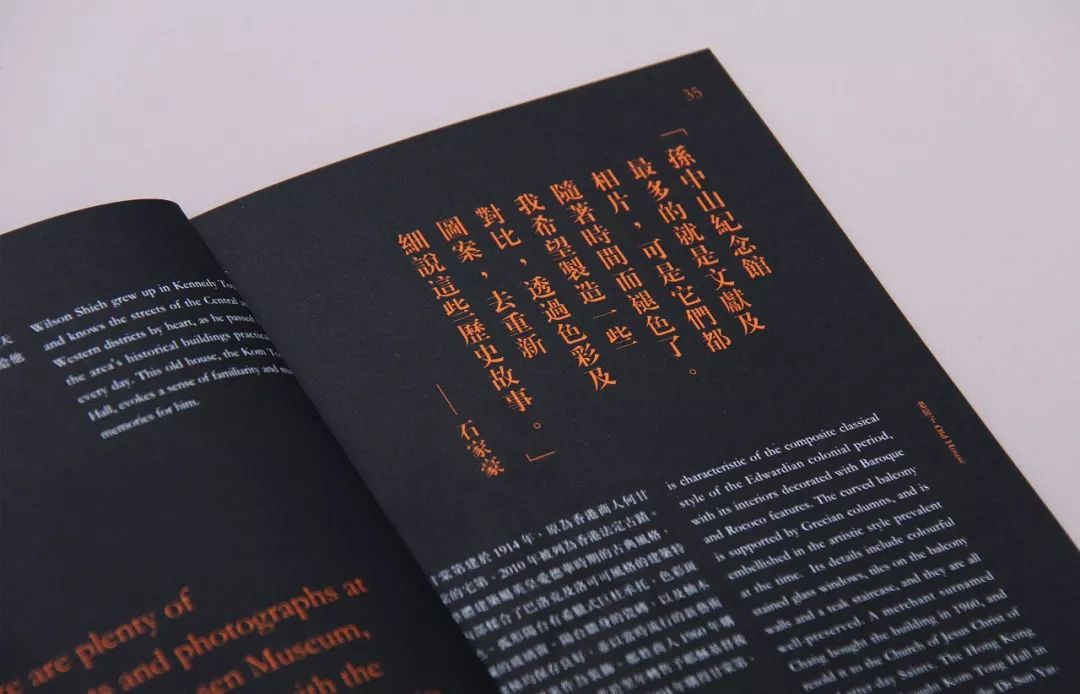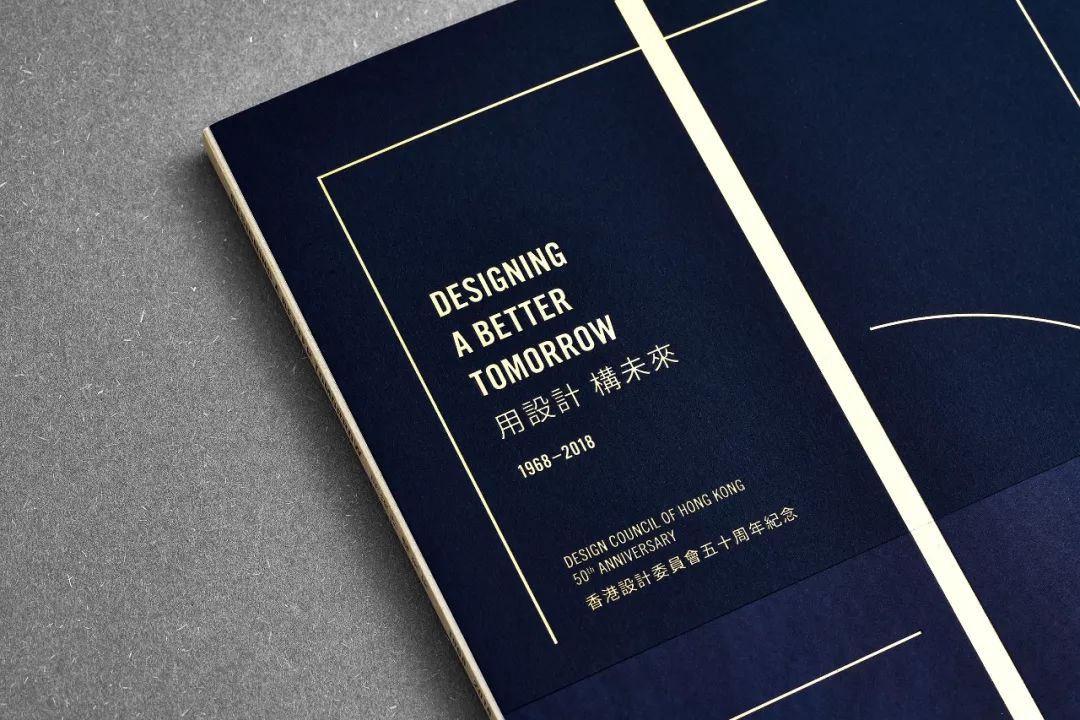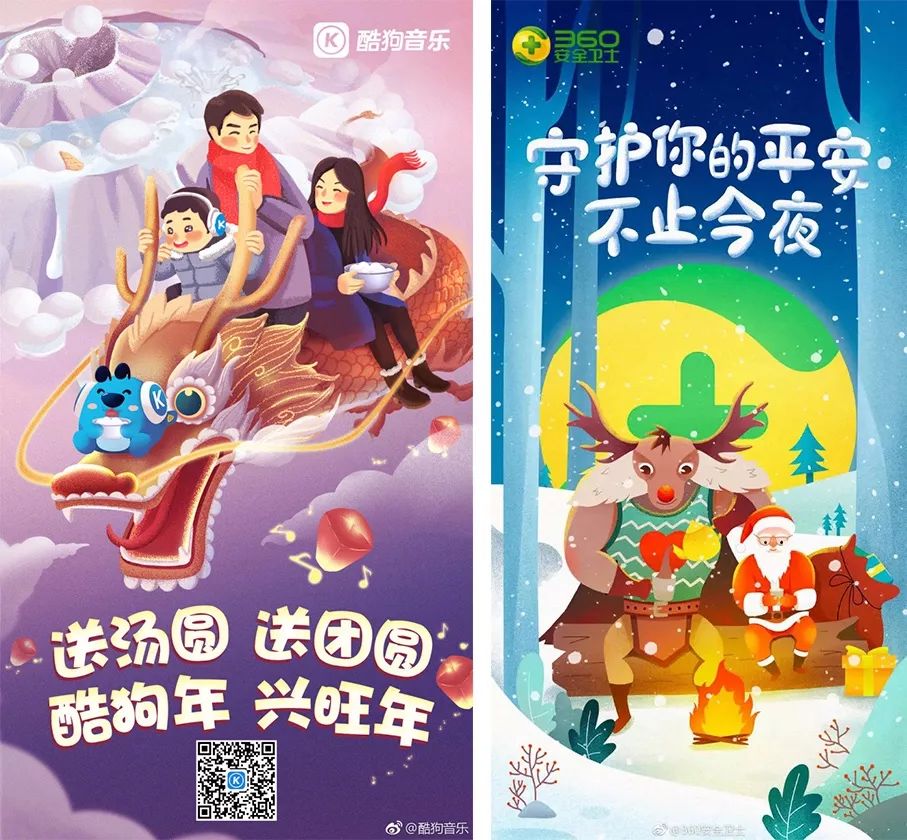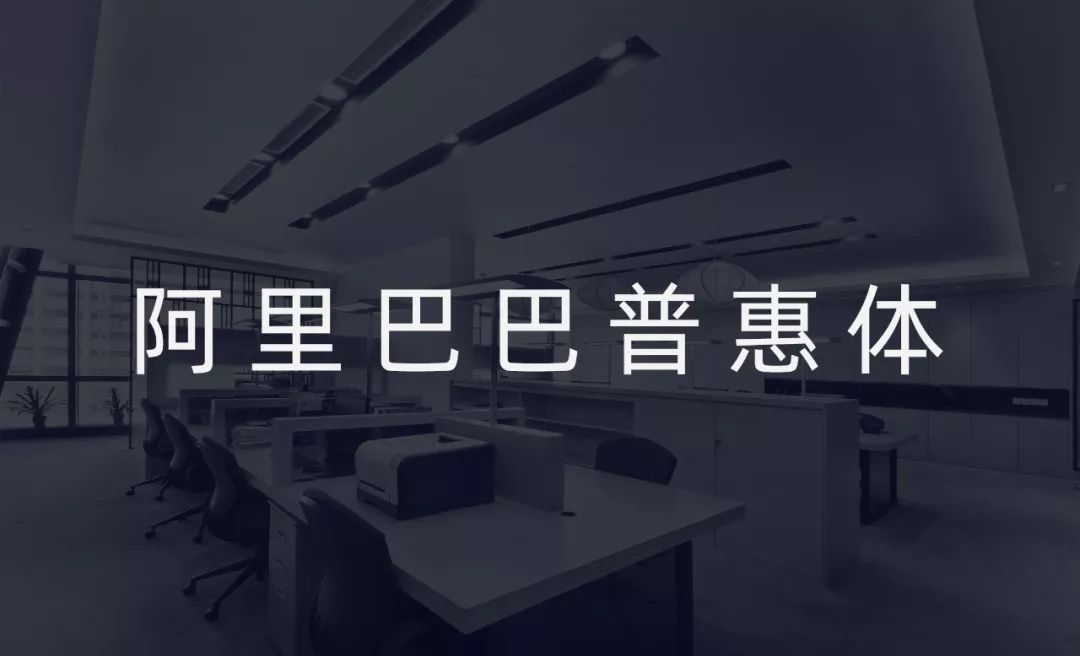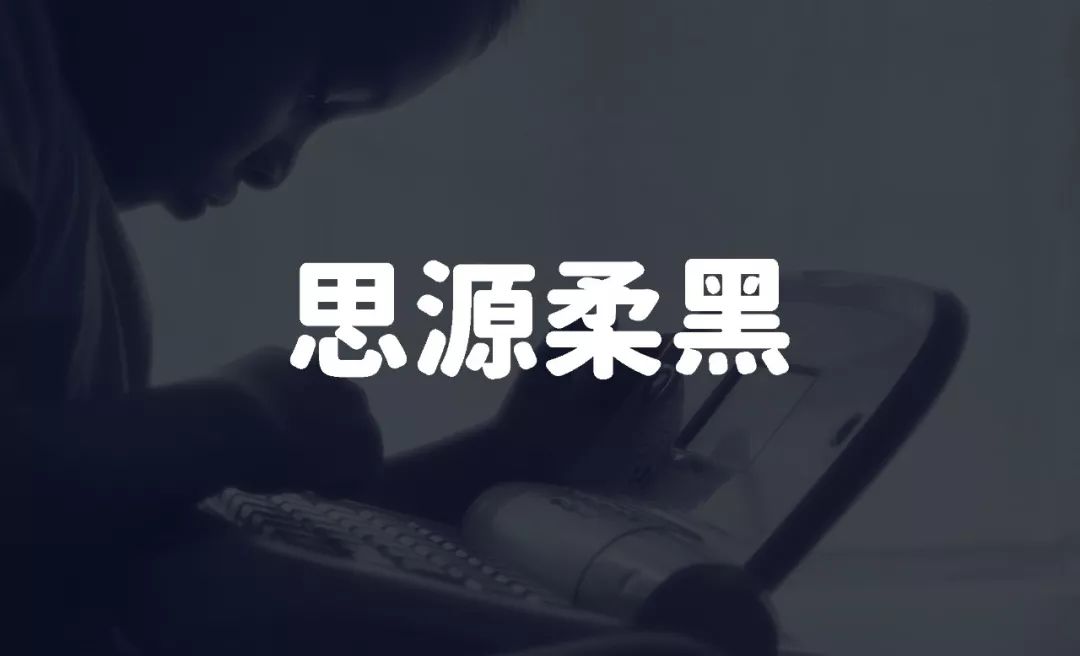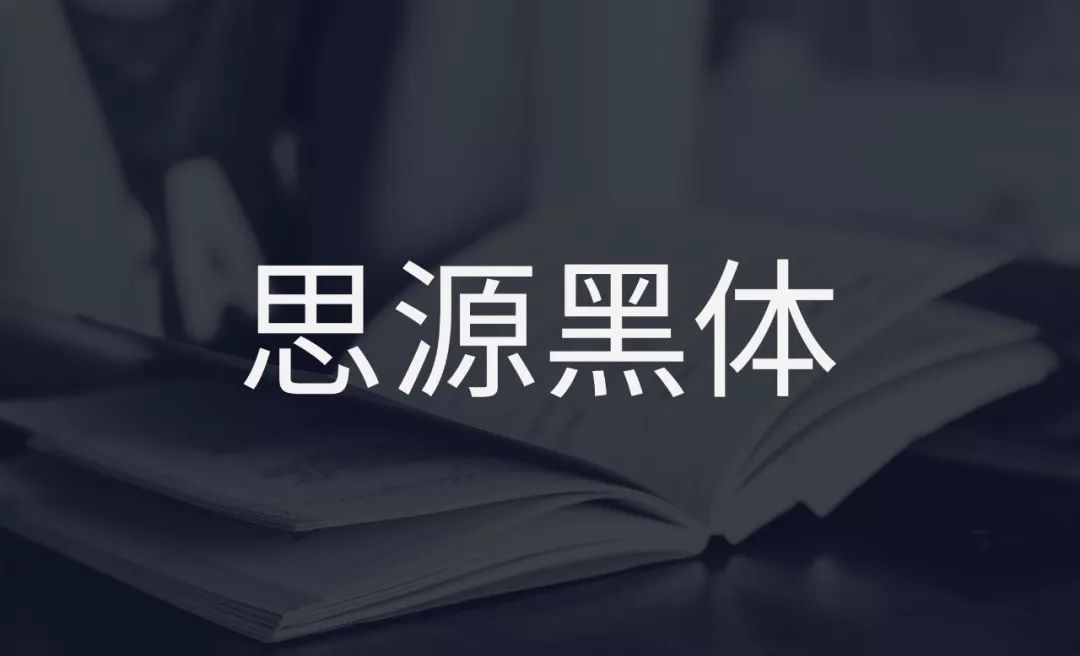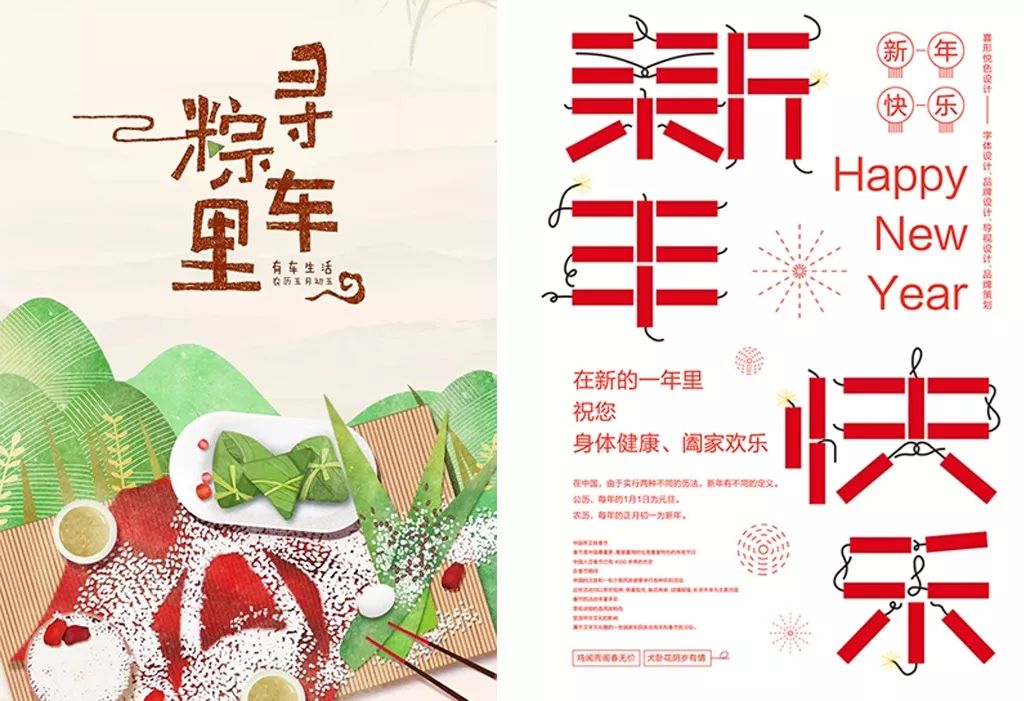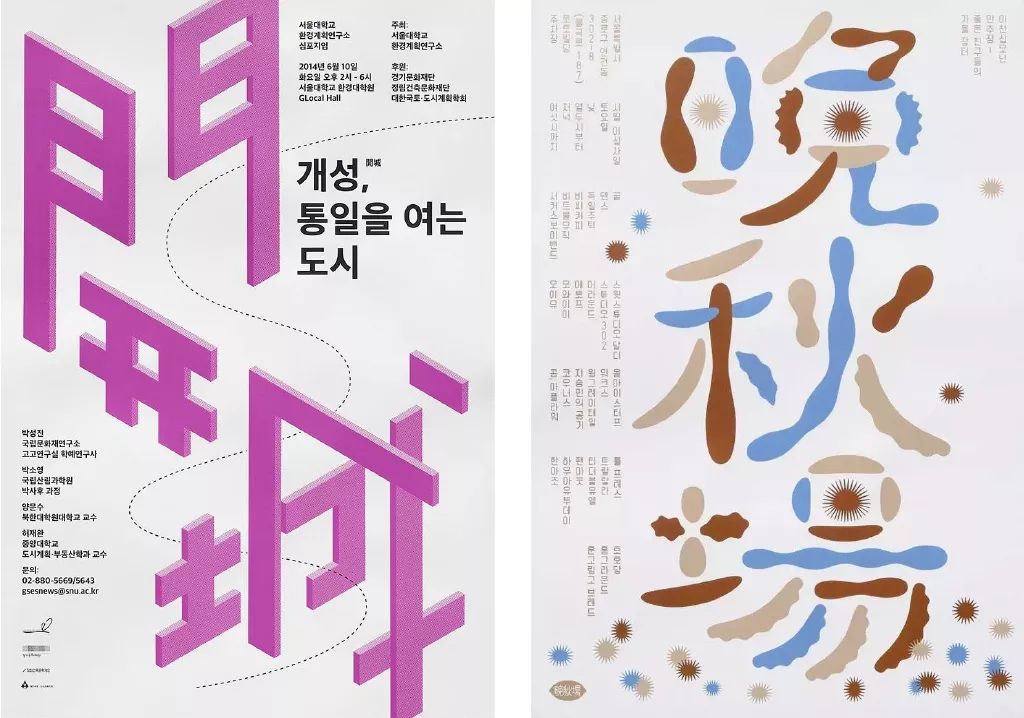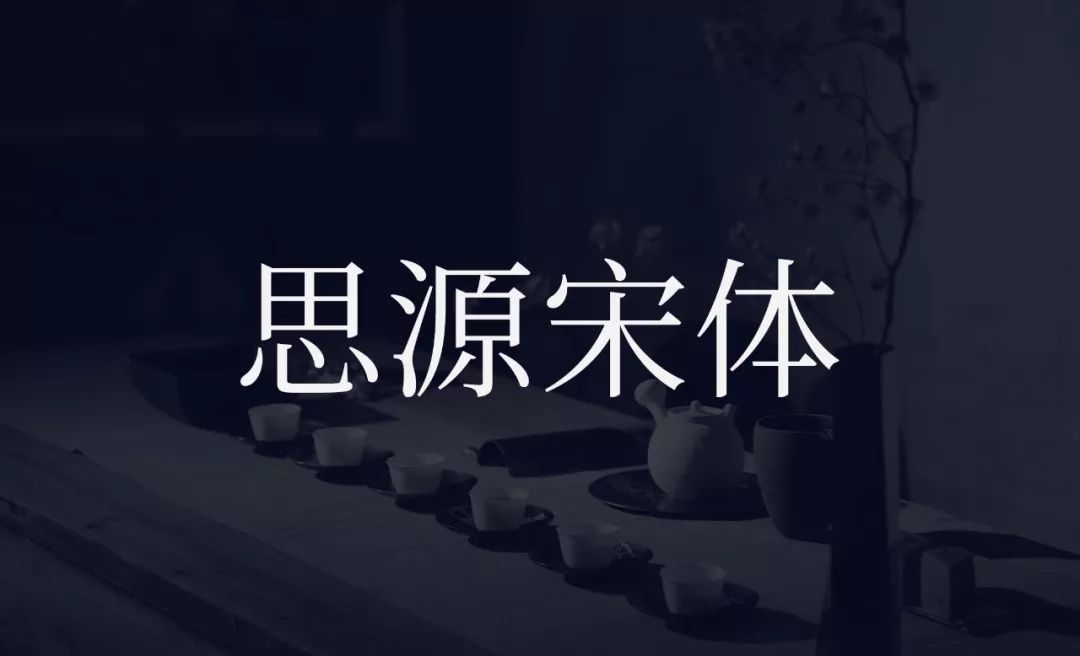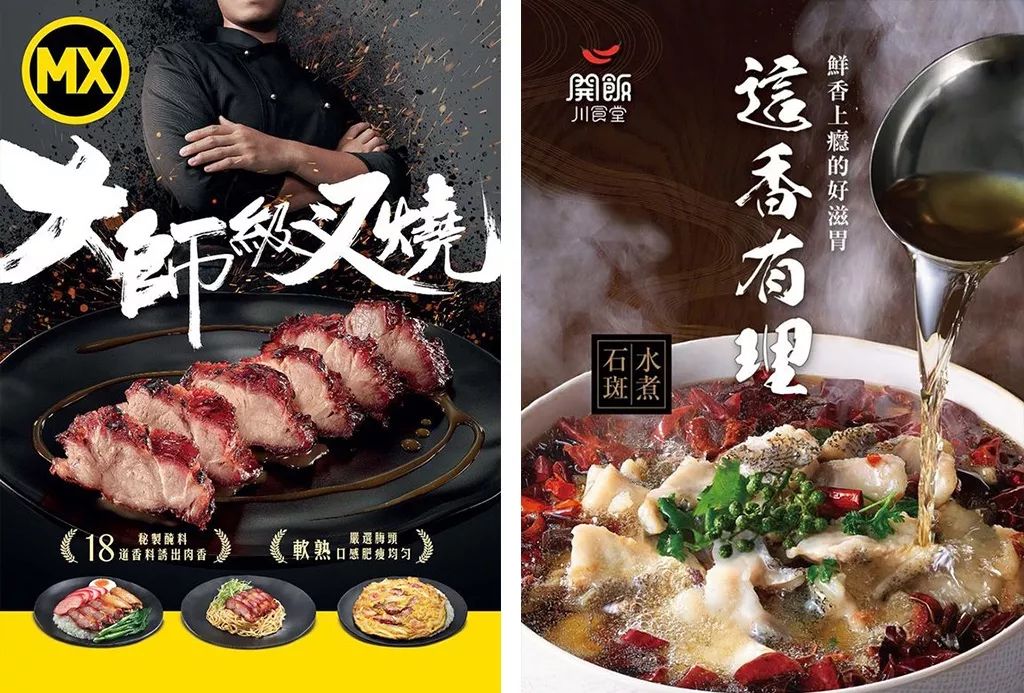
字体搭配技巧,做到字体和版面完美契合
对于设计师而言,为每个设计选择合适的字体是必须掌握的知识要点。如果你正在为“怎样选择合适的字体和有效地使用字体”而感到困惑,那么今天这篇文章可以让你通过一些简单的理论和经验,能轻松为设计选择合适的字体。
01
了解
字体气质特征
设计师在进行设计时,字体是否运用得合适,能直接决定版面的成败。选择合适的字体能准确地传达信息和美感,但是对于很多设计新手们来说,选择字体实在有点难度。原因是字库字体太多不知选择哪种,或者自我感觉字体越酷才是越好看,从而导致画面感档次不高。因此选择字体前需要了解各字体的气质特征,才能对症下药。
▲ 字体样式过多,导致画面凌乱,而且让信息不易识别
▲ 选择的字体种类过多,信息层级混乱和缺少主次
那么在选择字体之前,需要对字体性格有一个充分的了解,才能灵活运用。字体有很多种,我们可以将英文字体大致分为:衬线体、非衬线体、手写体和花体。中文字体目前还没有更系统的分类,一般分为:宋体、黑体、圆体、篆书、隶书、草书、行书等。这里我们对中文字体做大概的介绍。
◇ 黑体的风格特征
富有现代感、方正简洁、醒目的特征
无明显的情感表达,运用较广泛
◇ 黑体的适用范围
粗体字醒目突出,适用于画面感强烈,突出强调信息的用途
细体字精致简洁,适用于女性行业、时尚、科技、餐饮等类型内容
◇ 推荐字体
思源黑体、阿里巴巴普惠体、汉仪旗黑、微软雅黑、方正兰亭黑简体、蒙纳简黑体、文泉驿体
◇ 宋体的风格特征
拥有洋气的笔触,高雅显格调
具有较强的感情色彩,如历史感、秀气、文质彬彬等气质
富有深厚的文化底蕴
◇ 宋体的适用范围
粗体字醒目突出,适用于画面感强烈,突出强调信息的用途
细体字精致典雅,适用于时尚行业、奢侈品、女性行业等类型内容
适用于文化艺术、餐饮、养生、传统文化、地产等类型内容
◇ 字体推荐
思源宋体、方正颜宋简体、造字工房尚雅、造字工房俊雅、造字工房刻宋、日本花园明朝体、装甲明朝体
◇ 圆体的风格特征
富有活力和亲切感
饱满且带有圆润型的边角给人亲和感
◇ 圆体的适用范围
不建议作为大篇幅文段使用
一般适用于儿童,孕妇行业或气氛活跃、温馨的活动等类型内容
◇ 字体推荐
思源柔黑、锐字云字库圆体、方正兰体圆体、腾祥嘉丽圆简体、蒙纳简圆体、王汉宗简圆体
◇ 书法体的风格特征
造型丰富,自由性强
拥有洋洋洒洒的笔触,冲击感强烈
富有强烈的感情色彩
◇ 书法体的适用范围
不建议作为大篇幅文段使用,一般作为标题性用途
手写体的风格性极强,因此适用范围也较窄
书法字体主要包括篆、隶、楷、行、草
◇ 艺术体的风格特征
创造性和独特性较强,感情也较为丰富
使用的局限性较大,很难通用
◇ 艺术体的适用范围
不建议作为大篇幅文段使用,一般作为标题使用
适用于文化艺术、创造性强、特定主题等
艺术体例如有:综艺体、卡通体、涂鸦体、美术体等
02
03
怎样
与主题匹配
不同种类的字体代表不同的风格样式,是文字的表现形式和风格触感。在项目开始前,我们需要明确设计目的。例如:“项目面向的目标人群有哪些?设计风格是什么?是否需要和其他的设计、品牌相匹配?”等等这些问题。而这些问题将帮助你解决如何选择和使用字体的初步思路。
案例①
主题风格
温馨氛围和亲切感
↓
圆体或手写的儿童体
如果画面想表达一种温馨氛围和亲切感,那么字体可以选择圆体或手写的儿童字体。圆体饱满且带有圆润型的边角给人亲和感,而手写的儿童字体俏皮乖巧,笔画均匀圆润,感情也较为丰富,但不能选择笔画较为复杂的字体。
案例②
主题风格
现代简约、高格调
↓
黑体或宋体
黑体和宋体的共同点可以体现出现代简约、高格调的风格。但是需要注意字体的粗细,也就是文字的字重比例运用,应选择同家族字体的不同字重加以区分突出。粗体字带有强烈的视觉冲击力,可以突出强调信息,一般作为标题使用;细体字带有精致细腻之感,一般作为正文使用。
04
总结
在同一版面中不宜选择过多的字体,最好不超过三款。字体风格过多容易导致凌乱、缺乏重点,应选择同家族字体的不同字重加以区分突出。平时要多留意优秀设计作品中的字体应用,开阔眼界和加深对字体的了解。也希望今天的文章对字体选择有困难症的同学带来帮助。